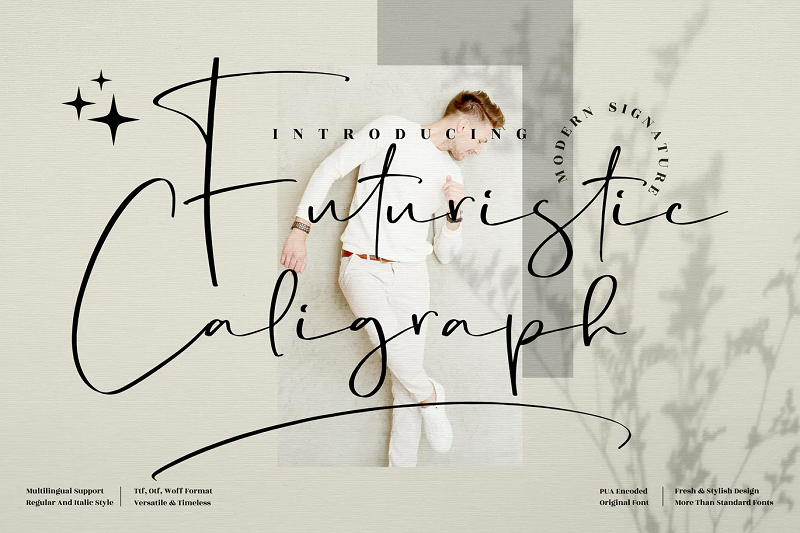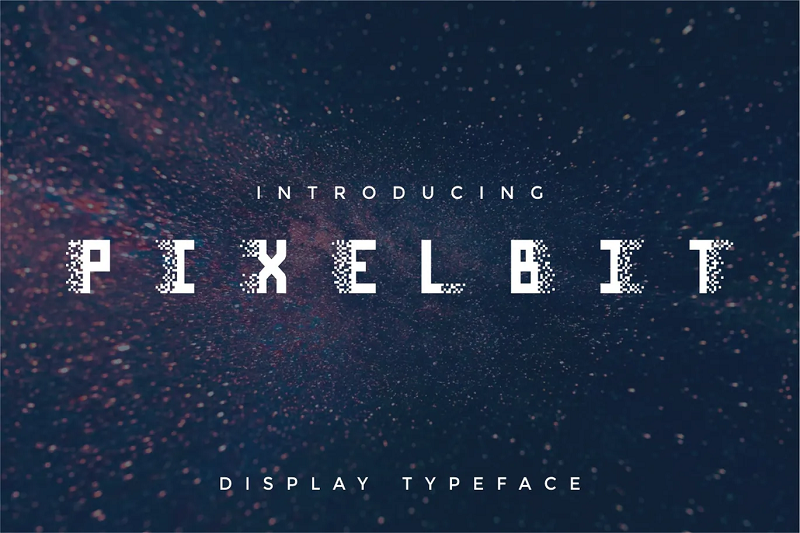
44 futuristische Schriftarten, die nicht von dieser Welt sind (2022)
Veröffentlicht: 2022-03-08Arbeiten Sie an einem modernen, innovativen Designprojekt und suchen Sie nach einer Schriftart, die zu Ihnen passt? Wir geben dir Deckung.
In diesem Beitrag stellen wir 44 der besten verfügbaren futuristischen Schriftarten vor, die ihrer Zeit weit voraus sind. Alle Schriftarten auf dieser Liste sprengen die Grenzen der Typografie und sind vollgepackt mit visuellem Interesse.
Top 44 der besten futuristischen Schriftarten
1. Varino – Unsere Top-Auswahl
Varino ist unsere insgesamt beliebteste futuristische Schriftart. Es verfügt über ein minimalistisches Design mit einzigartigen Buchstabenformen, die mit unseren Erwartungen an das Aussehen von Schriftarten spielen. Der Designer ließ sich von moderner Technologie, Science-Fiction-Filmen und Gadgets inspirieren.
Warum es unsere erste Wahl ist
Varino ist eine futuristische Schrift schlechthin. Es folgt einem klassischen SciFi-ähnlichen Design, das an Weltraum, Wissenschaft, Technologie und alles Futuristische erinnert. Dadurch ist es sehr vielseitig – es würde in jedem modernen Designprojekt gut funktionieren.
2. Metropole
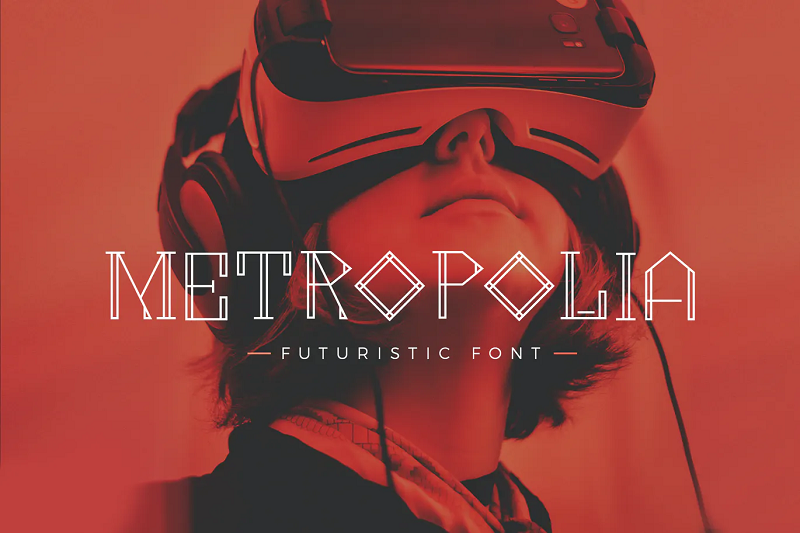
Als nächstes haben wir Metropolia. Diese geometrische futuristische Schriftart verwendet gerade Linien und Doppellinienstriche, um einzigartige Buchstabenformen zu erstellen. Buchstaben, die traditionell rund sind – wie das „o“ – und Schalenstriche werden stattdessen aus geraden Linien konstruiert.
3. Aceton
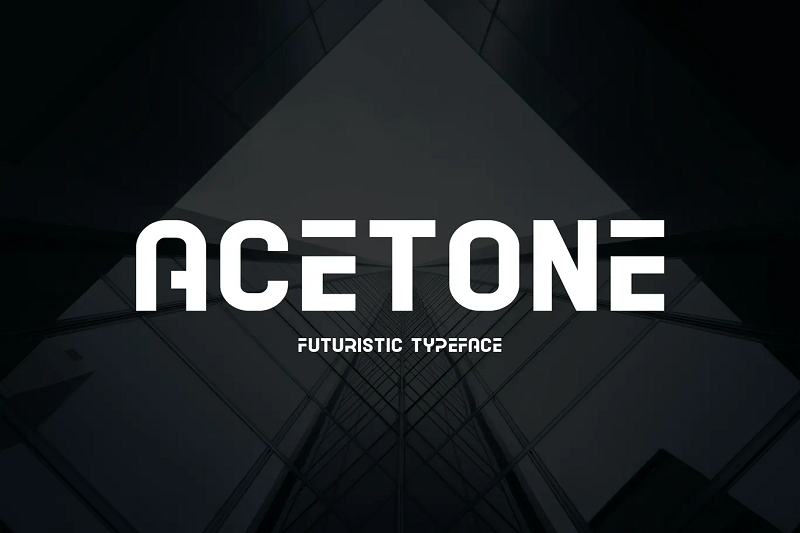
Acetone ist eine minimalistische, futuristische Schrift ohne Schwünge oder ausgefallene Schnörkel. Es ist eine Schriftart, die mit dicken Strichen und abgerundeten Armen wirklich Eindruck macht und sich hervorragend für Logos, Buchumschläge und mehr eignet.
4. Zenturio
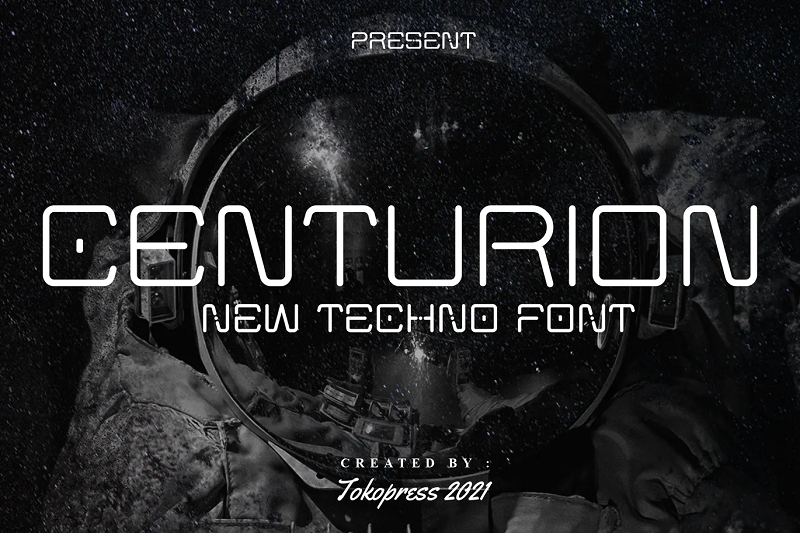
Centurion ist eine weitere coole futuristische Schriftart mit abgerundeten Enden und dünnen Strichen. Zähler und Schalen in Buchstaben wie „o“ und „c“ werden mit inneren Details akzentuiert, wodurch ungewöhnliche Buchstabenformen entstehen. Diese Schriftart eignet sich perfekt für futuristische Designs wie SciFi-Filmplakate, Wissenschaftsmagazine und Spiel- und Buchumschläge mit Weltraummotiven.
5. Volt
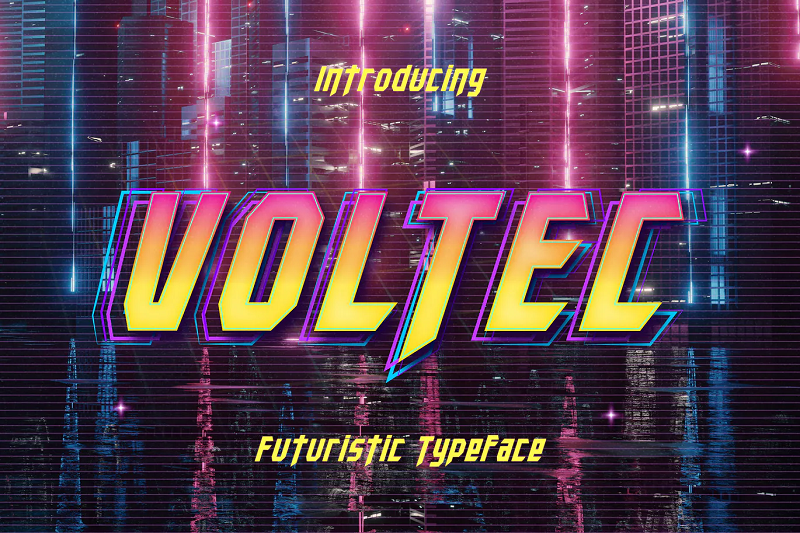
Voltec ist eine nostalgische, retrofuturistische Schrift im Cyberpunk-Design der 80er Jahre. Etwas an dieser Schriftart ist vage nostalgisch. Es erinnert an helle Neonlichter und Stadtlandschaften und schafft eine sehr spezifische Ästhetik, die in bestimmten Designs gut funktionieren würde.
6. Anurati
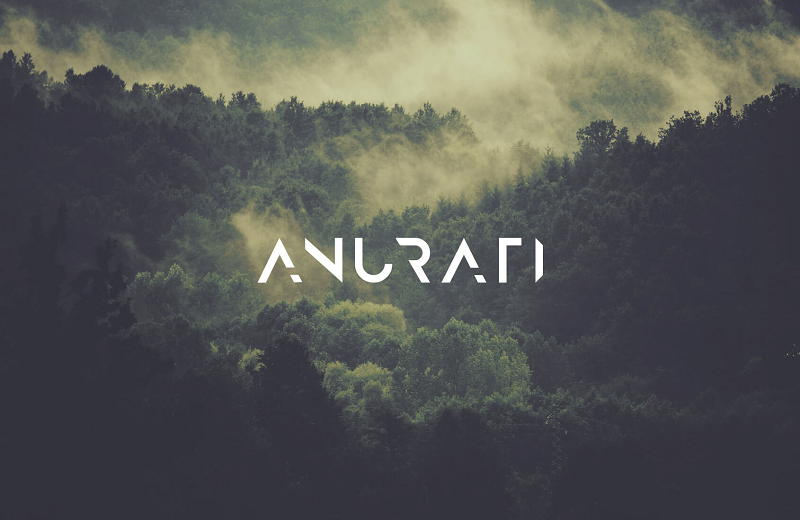
Anurati ist eine sehr beliebte kostenlose Schriftart mit über 700.000 Downloads. Es weist fehlende Balken und vertikale Striche auf, um interessante Buchstabenformen zu schaffen, die ihm eine futuristische und dennoch minimalistische Ästhetik verleihen. Die Verwendung in Ihren persönlichen Projekten ist kostenlos, aber wenn Sie es für kommerzielle Projekte verwenden möchten, müssen Sie die Pro-Version erwerben.
7. Ischimura
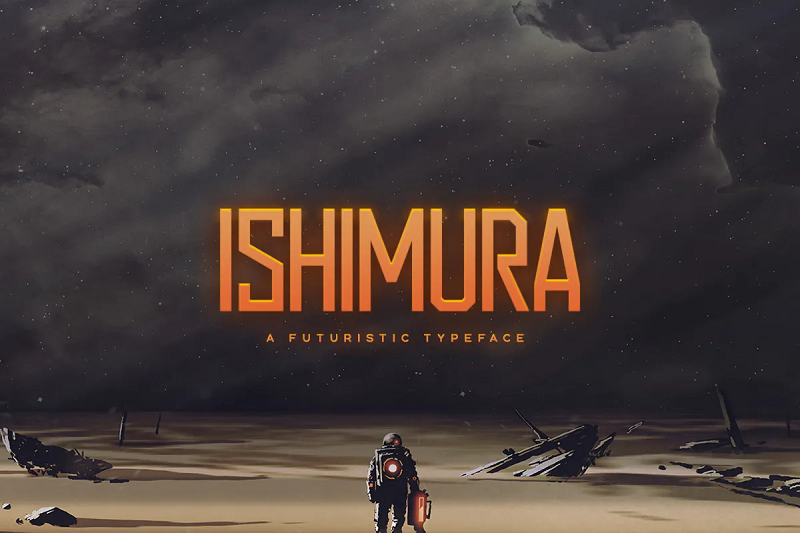
Ishimura ist eine industrielle, futuristische Schrift, die von klassischen SciFi-Designs inspiriert wurde. Der japanische Schriftname „Ishimura“ bedeutet wörtlich übersetzt „Steindorf“. Diese Schriftart eignet sich hervorragend für SciFi-Bücher, -Spiele und -Manga.
8. Durchschnitt
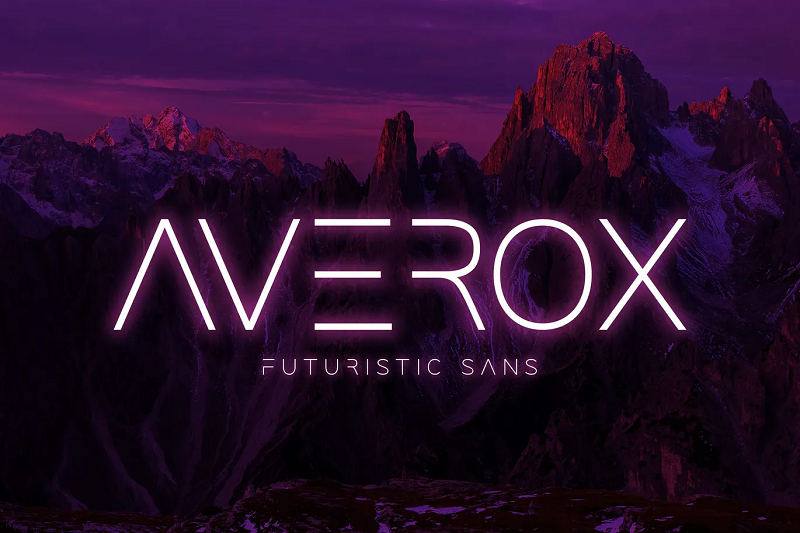
Averox von Alterzone ist eine weitere futuristische Sans-Schriftart mit minimalistischem Design. Es zeichnet sich durch dünne Striche und fehlende Balken und Unterlängen aus. Es würde gut in Modedesigns, Logos, Branding und Broschüren funktionieren.
9. Atomblitz
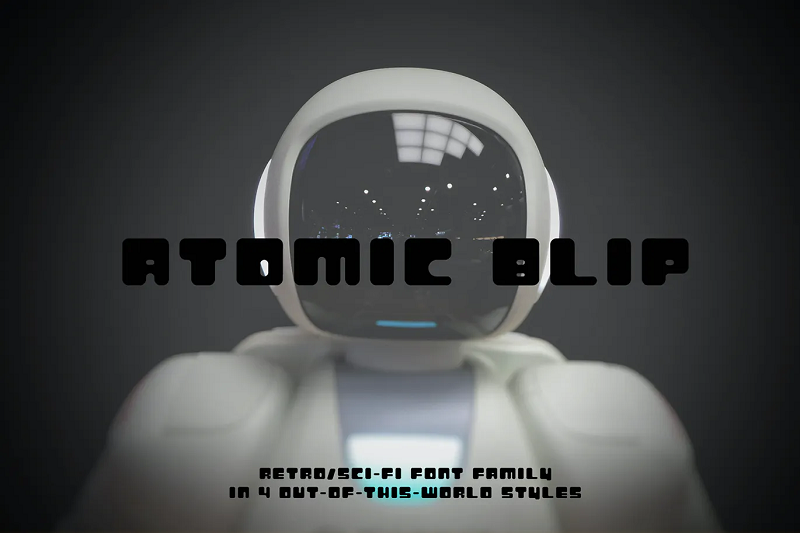
Atomic Blip schafft es, zwei gegensätzliche Ästhetiken perfekt zu verschmelzen: Retroismus und Futurismus. Es schafft es irgendwie, beides gleichzeitig zu sein, was diese Schriftart zu einer wirklich interessanten Wahl macht.
Es ist eine lustige Schriftart mit abgerundeten Buchstabenformen, dicken Strichen und winzigen Zählern. Das Schriftartenpaket umfasst AZ, Zahlen und Satzzeichen und ist in vier Familien (gerundet, quadratisch, umrandet und gestrichelt) erhältlich.
44. Trixie
Trixie ist eine futuristische Schichtschrift. Mit geschichteten Schriftarten können Sie Text mit verschiedenen Schriftstilen und Farbvariationen „überlagern“, um einzigartige 3D-Effekte zu erstellen, die Ihre Designs hervorheben. Trixie verwendet eine moderne, klare Ästhetik und ist vielseitig genug, um in vielen verschiedenen Arten von Designs gut zu funktionieren.